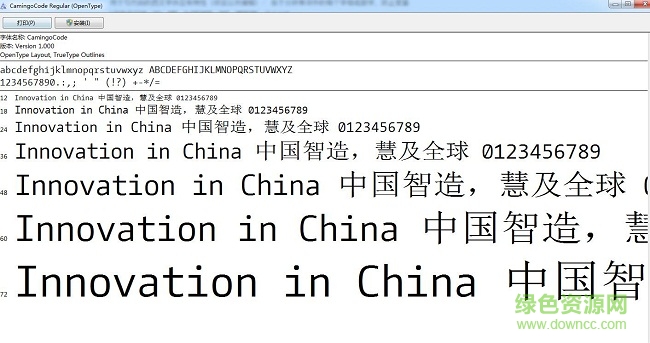
camingocode 字體是一款適合用于代碼的優(yōu)秀等寬字體,字形清晰,識(shí)別度高,排版效果自然流暢,這款字體看大段代碼比較方便,不傷眼睛,需要的朋友快來(lái)下載吧!
等寬字體(monospaced font)是指字符寬度相同的電腦字體。東亞語(yǔ)言中,方塊字基本上都作為等寬字體處理,如各個(gè)地區(qū)的漢字、日語(yǔ)假名的全形字符、韓語(yǔ)諺文音節(jié)等字符都是等寬的。